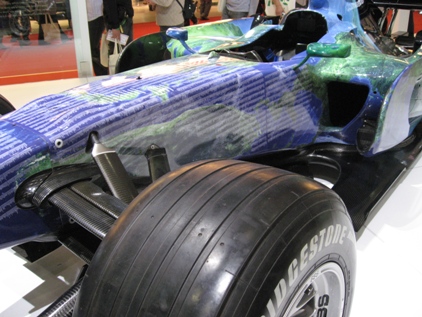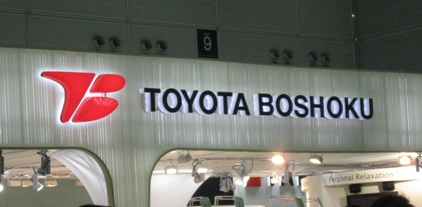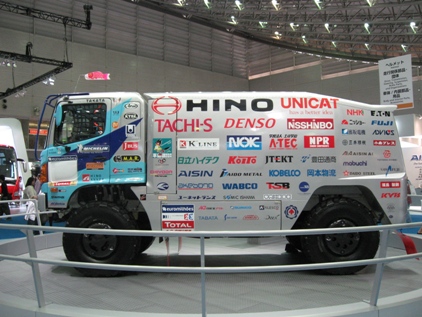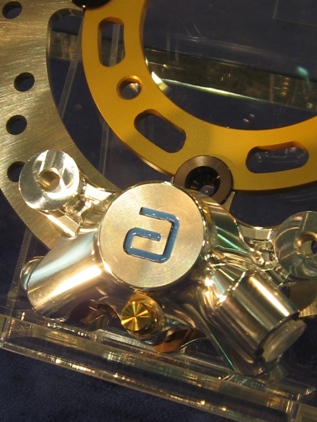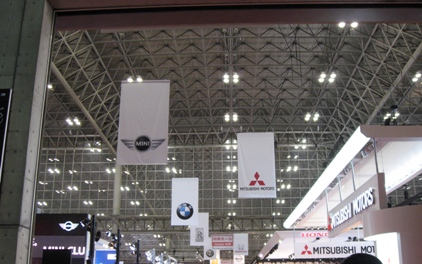
モーターショーでロゴ探し
ここにくれば、素敵な車、見たことのない部品、きれいなお姉さん、
そしてロゴが勢ぞろいです。
何と言っても世界中に通用するロゴですものね・・・。
最初に見えたのが「HINO」のトラックです。これは、ダカール・ラリーに参戦しているもの・・・。これだけのスポンサーが必要なんですね!
ロゴだらけ〜。運転席の上方に鯉のぼりがハタハタ・・・。
これは、TOYOTA BOSHOKUのTとBが合わさっているロゴですね。
TACHI−Sはスプリングの会社。
ロゴの上にあるマークが可愛いです。
スプリングのマーク・・・ですね。
aの一文字がきれい!
これはブレーキメーカーのAKEBONO、
昔は曙でしたが・・・。
隠れた名品たちです。今年は、F1のマクラーレンに供給していたそうです。凄いですね〜!
日産のコーナーは、スカイラインのGTRがお披露目されていて、人だかりができていました。やはりお尻のライトは丸くなくちゃ!
三菱の車は電気自動車?
コンセントのデザインがわかり易くてこちらも可愛いですね。
偉そうな車は、MYBACHA・・・。Mのデザインがお高い?
値段を見たら・・・「ひゃぁ〜6千万!どうします、お嬢さん?」
イタリアのメーカーは、内装の革をディスプレーに使用〜。きれいな色です!
ちょっと敵いませんねぇ〜。さすが革の国!
二輪部門の方が車体のロゴが可愛いですね。小文字のiの頭が色っぽいおめめになっています。
TRIUMPHはRの足が〜Hの横棒になってます・・・。英国のメーカー・・・知りませんでした!
右の二輪はHONDAで、市販予定だそうです。かっこいい!
miniのブースはお兄さんがmixしてました。
音楽に合わせて壁面の模様も変わり、
車体に映りこんでいます。きれい〜。
ここは、若者にすごく人気がありましたね。
miniは車も可愛いし、全体的に
おしゃれ感が出ていて・・・だから人気が
あるのですね〜。
HONDAのF1カーです。
今年は環境の意識を高めるために
スポンサーロゴはなく、地球カラーで
した。この白い細かい文字は・・・、
寄付した人の名前だそうです。
でもでも、すごく近くに寄っても読めませんでした・・・。ちっちゃ!
HONDAも混んで・・・って、
何故か・・・近づいてみて
ようやくわかりました!
コンセプトカーのPUYOですが、
車体がプヨってしてるんですね。
車も可愛い!
でも一番人気はそう
ASIMO君でした!動いて、走って
一生懸命に宣伝してました!
きれいなお姉さんよりも、高級外車よりも・・・ASIMO君・・・一番人気かと!
mojitor-sさんが古本市で嬉々としている時に、hは「アシモ〜」と応援しているのでした。